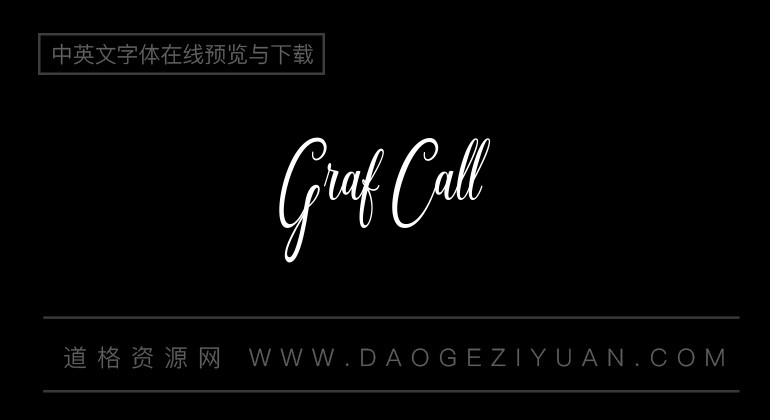
Graf Call
? Graf Call 字体是一款英文字体,由美国设计师Graf Call创作。它具有清新、活泼、简洁的外观,给人一种极具生机的感觉。字体具有细腻的线条,拥有一种温暖的质感,是一款优雅大方的字体。Graf Call字体可以用于创作文字、印刷、网页设计、平面设计等多种场景,可以提升文字的视觉效果。
Graf Call是一款非常不错的手写艺术字体,具有很好的视觉感,适合于文化类的宣传设计、商业类品牌的广告和产品包装设计以及个性化文字排版等较多场景。